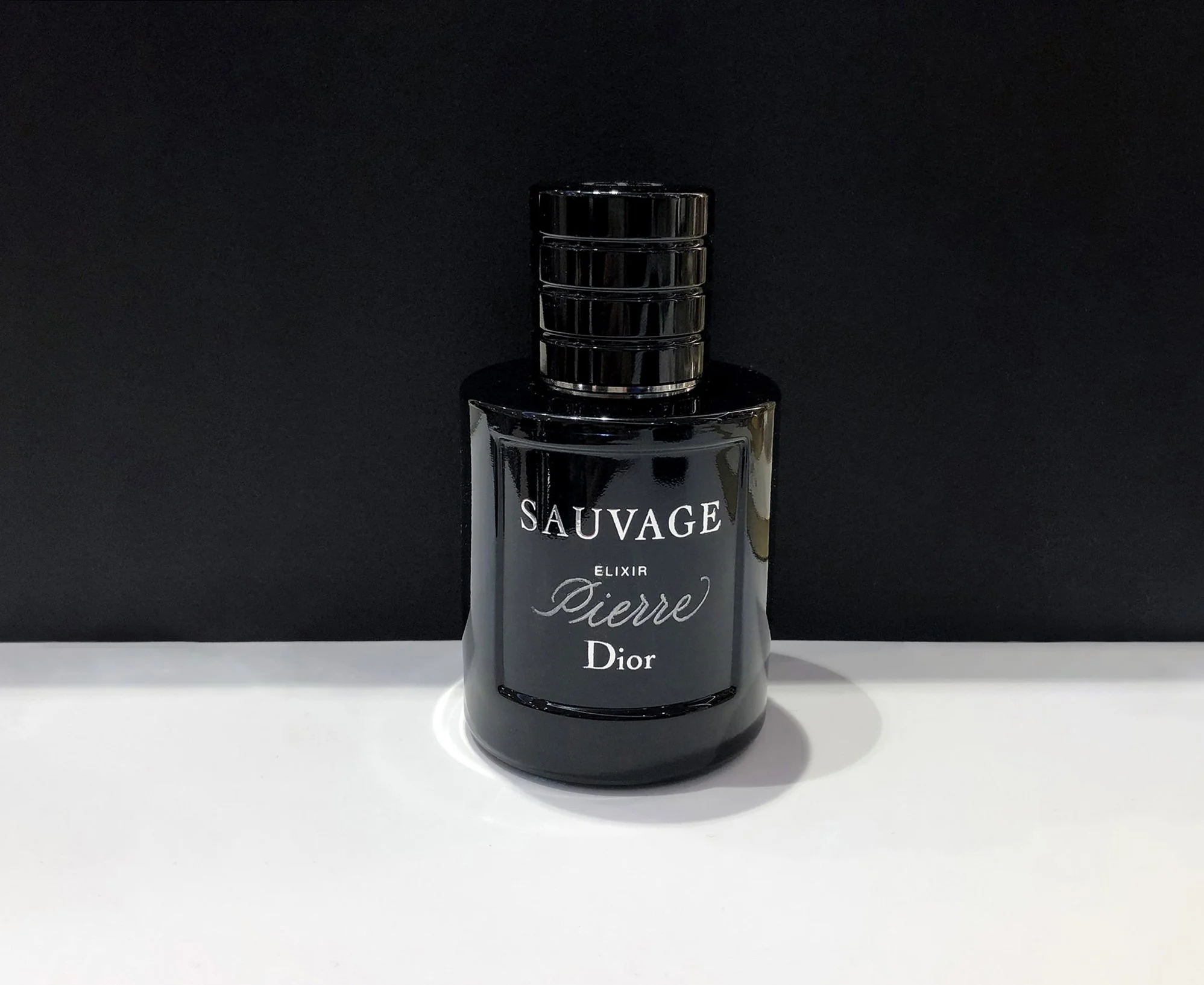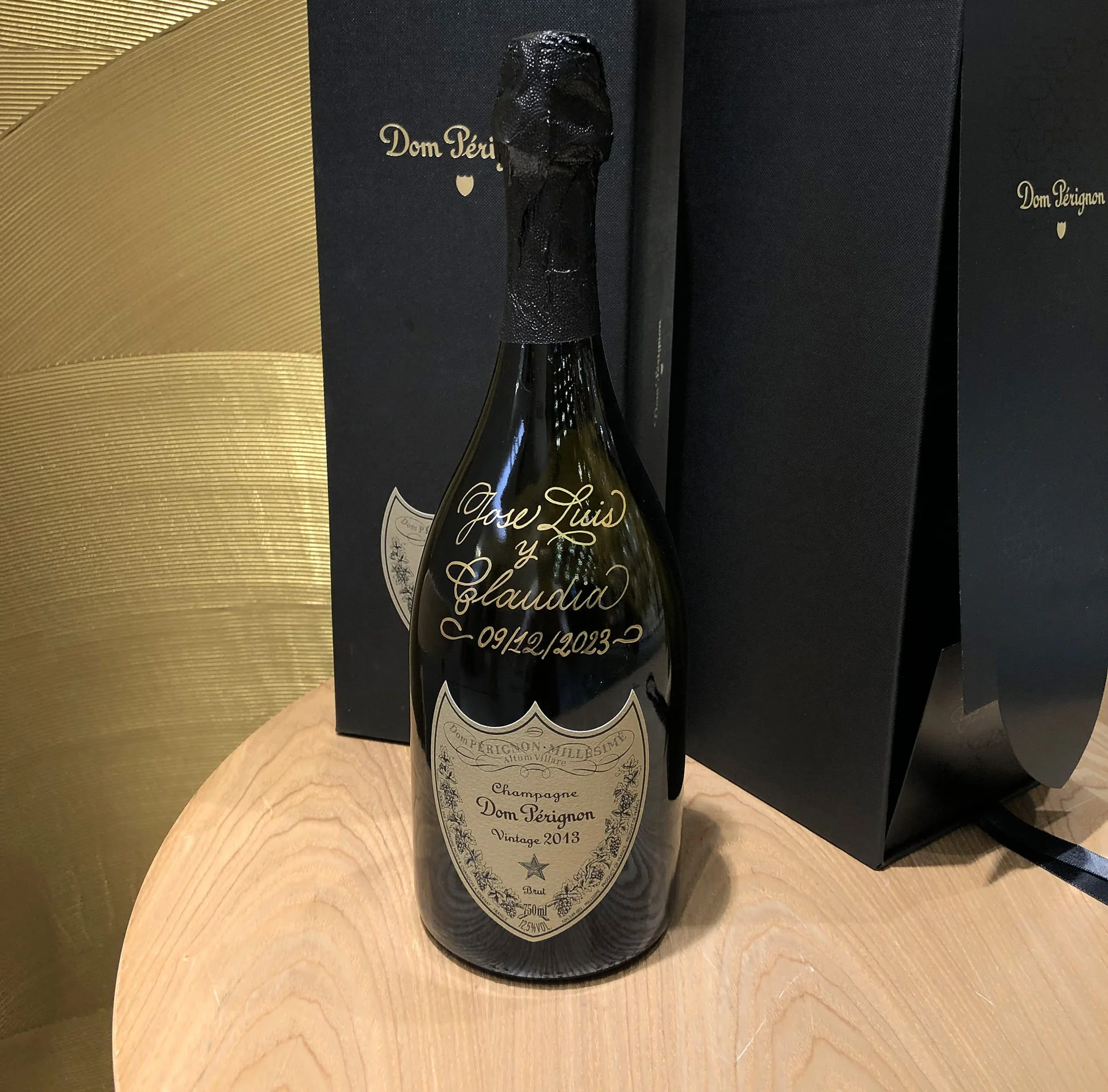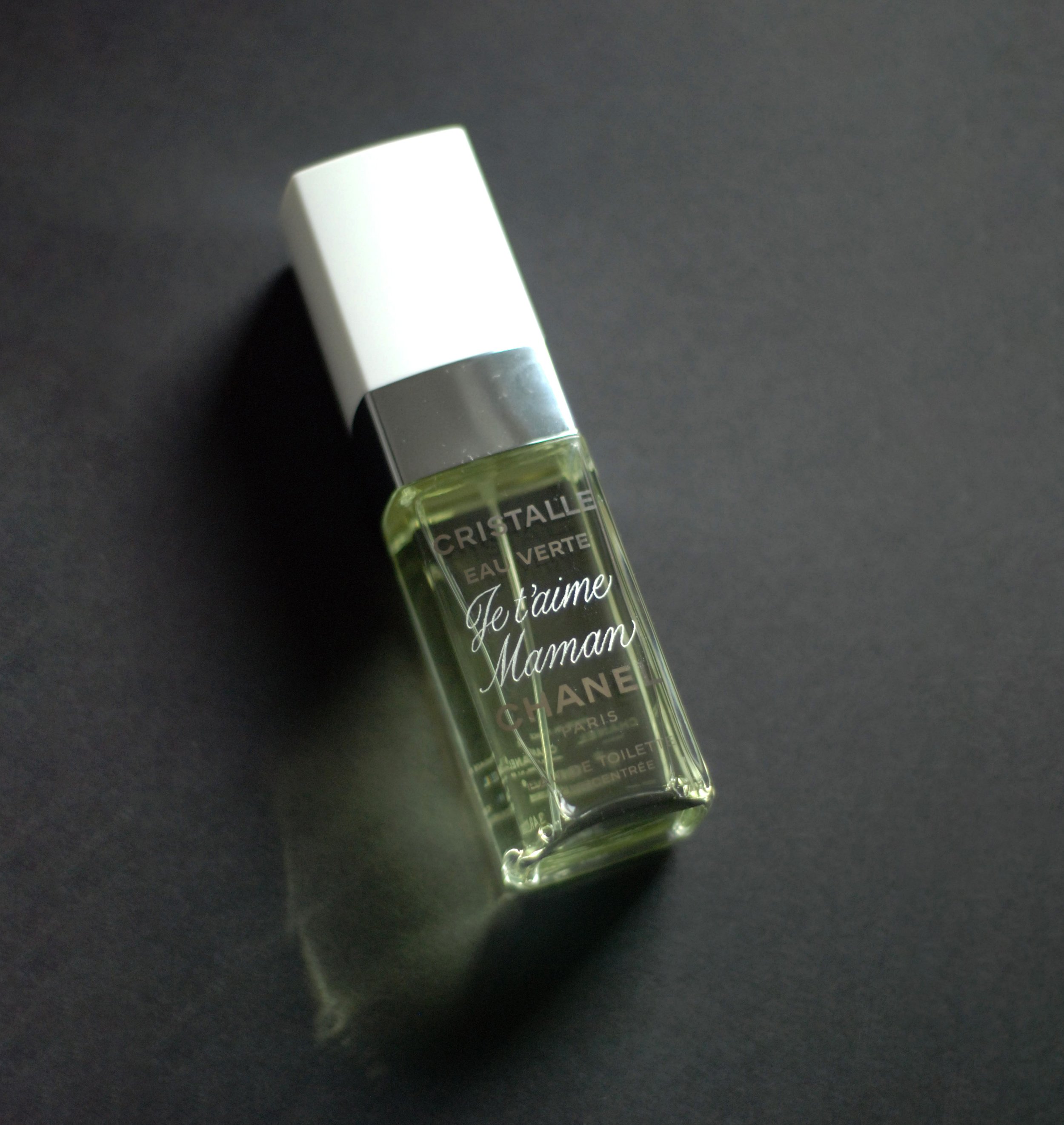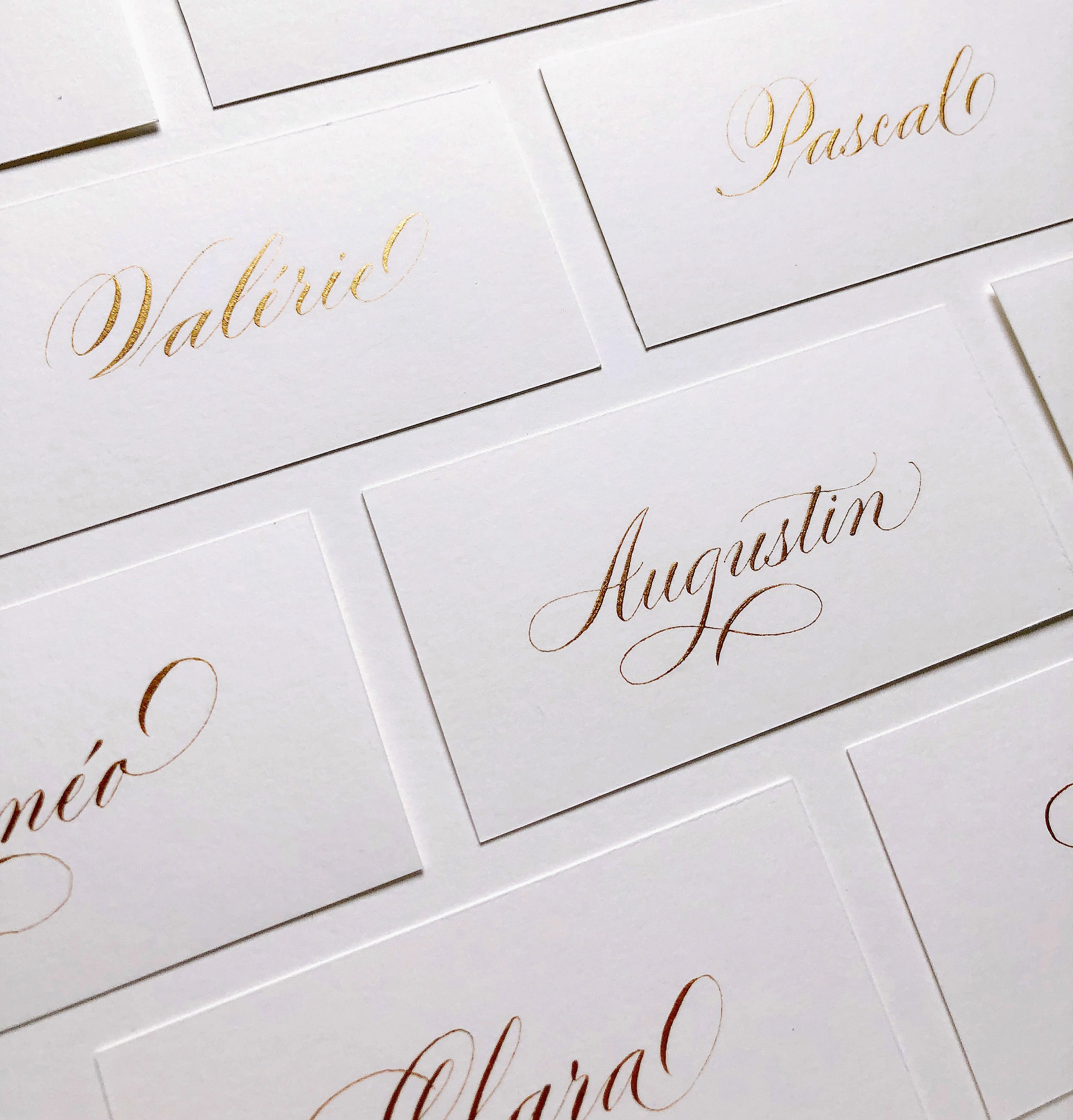
Calligraphie & lettrage
Lettrage réalisé à la main pour des supports papier — cartes, enveloppes, menus et éléments liés à l’événement. Je travaille à partir de styles classiques ou contemporains, choisis avec attention en fonction de la lisibilité, du ton et du contexte dans lequel ils s’inscrivent.
Gravure
Gravure sur site sur verre, métal, flacons de parfum et matériaux sélectionnés. Chaque pièce est personnalisée à partir de formes de lettres dessinées à la main, créant un détail durable et tactile, pensé pour marquer les esprits.
Contextes d’intervention
Animations en boutique et personnalisations en point de vente
Lancements de produits et événements parfum
Cadeaux de marque et occasions spéciales
Campagnes saisonnières et célébrations
Matériaux & Surfaces
Verre
Métal
Flacons de parfum
Papier
Cuir
Matériaux spécifiques sur demande
Chaque surface demande une approche spécifique. J’accorde une attention particulière à la manière dont les lettres évoluent dans le temps, captent la lumière et se perçoivent au toucher, afin de garantir une gravure à la fois lisible et durable.